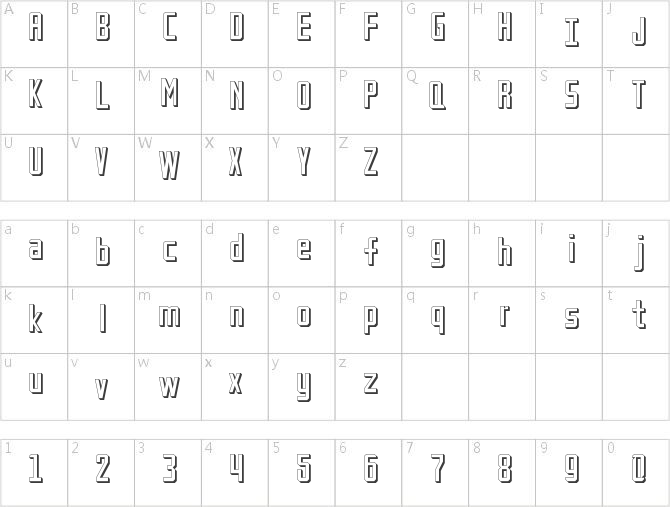
字体名称: PetakSq
PetakSquareShadow-Regular
PetakSquareShadow-Regular介绍
PetakSquareShadow-Regular字体字库是一款让人赏心悦目、百看不厌的英文字体,适合各类广告和产品包装设计应用,字体大小0.02MB,格式为ttf字体,上传用户是小黑,作者/版权方为未知